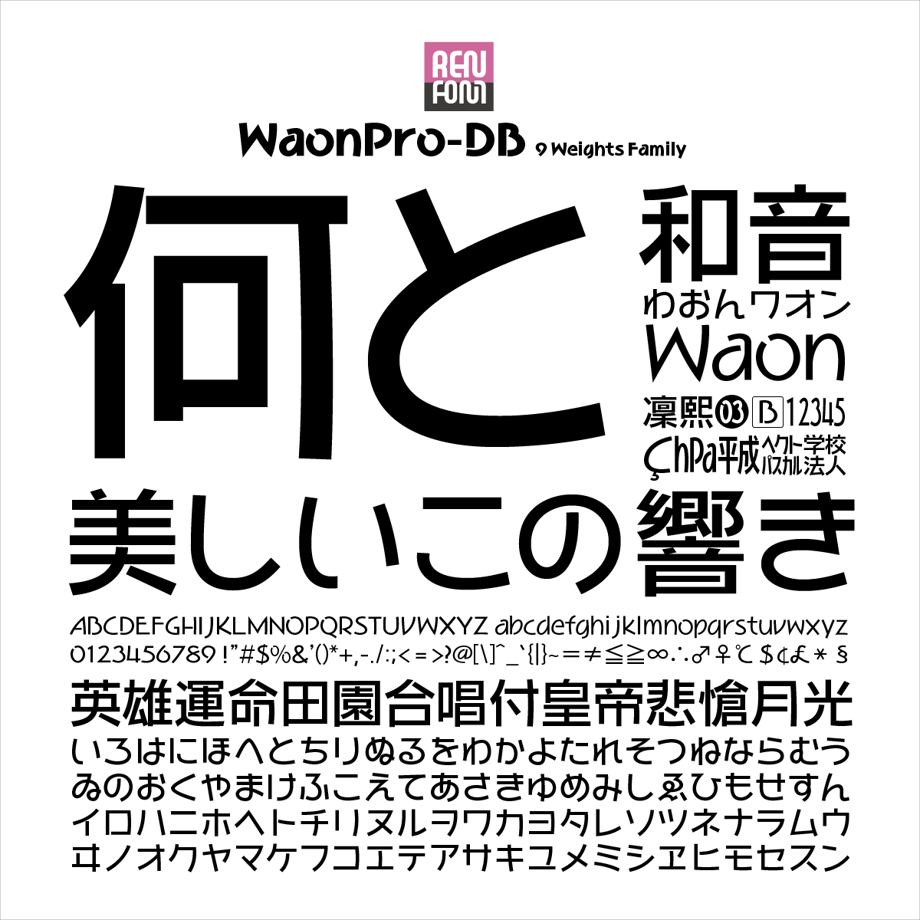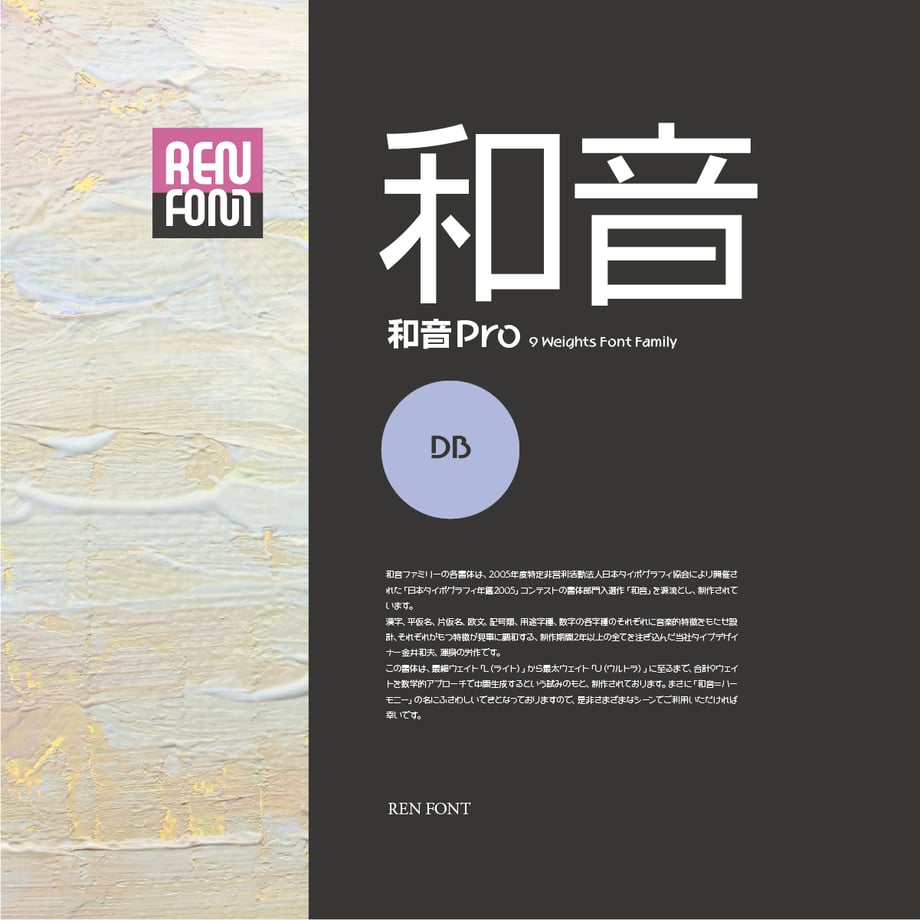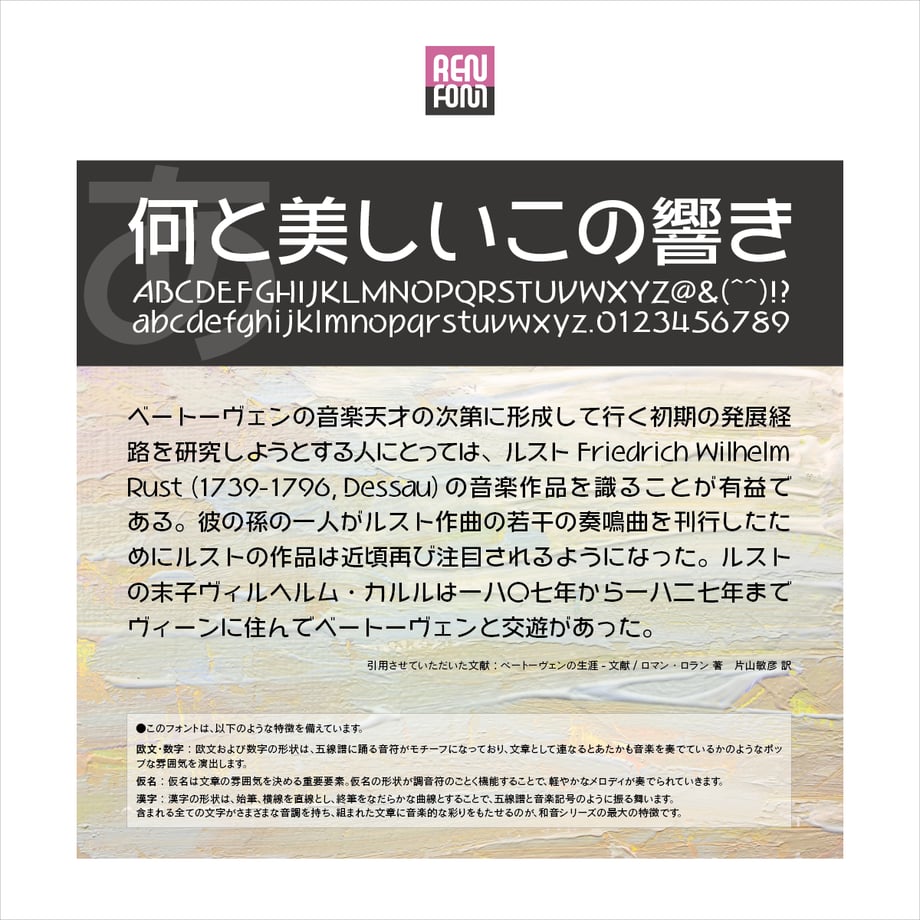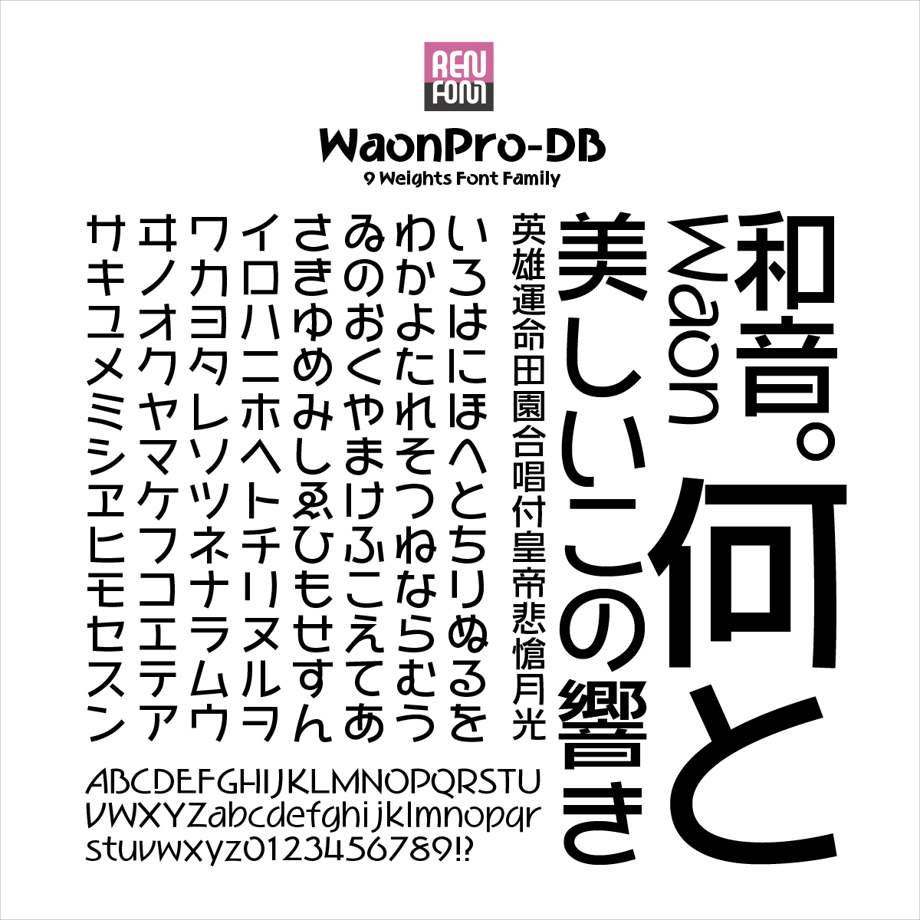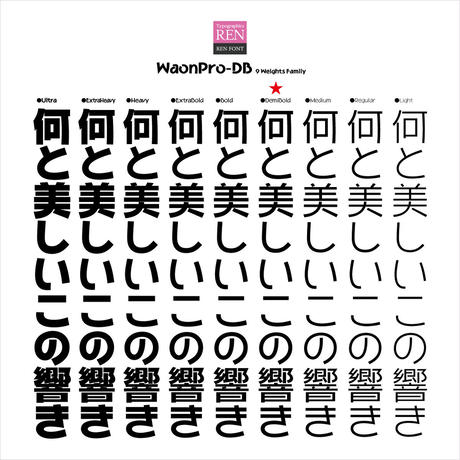
オールマイティな使用感のフォント
和音Pro 9ウェイトファミリー / OpenType
和音ファミリーの各書体は、2005年度特定非営利活動法人日本タイポグラフィ協会により開催された「日本タイポグラフィ年鑑2005」コンテストの書体部門入選作「和音」を源流とし、制作されています。
漢字、平仮名、片仮名、欧文、記号類、用途字種、数字の各字種のそれぞれに音楽的特徴をもたせ設計、それぞれがもつ特徴が見事に調和する、制作期間2年以上の全てを注ぎ込んだ当社タイプデザイナー金井和夫、渾身の労作です。
この書体は、最細ウェイト「L(ライト)」から最太ウェイト「U(ウルトラ)」に至るまで、合計9ウェイトを数学的アプローチで中間生成するという試みのもと、制作されております。まさに「和音=ハーモニー」の名にふさわしいできとなっておりますので、是非さまざまなシーンでご利用いただければ幸いです。
●EH[エクストラヘビー]
●漢字
ほとんどの文字のどこか1か所が切れて離れたデザインになっており、スタッカートのようなアクセント豊かな効果が生まれます。
また、終筆の跳ねをなくして緩やかな曲線しました。これは、指揮者が振り下ろし振り上げるタクトの軌跡を表現しています。 すべての文字に伸びやかさとおおらかさを与え、組まれた文章に音楽的な彩りや愉しさをもたらします。
文章の約70パーセントを占めるといわれる仮名。作品の雰囲気を決める重要要素といって過言ではありません。
音楽に欠かせないリズムを表現するために、終筆をあえて中途半端な長さに終わらせて不安定にし、和音と相反する「不協和音」を表現し、動きを与えました。
まるで音符のように機能し、オペレッタのような、可愛らしく軽やかなメロディが奏でられていきます。
「和音」の基本コンセプトである「文字で音楽を表現する」を、最も端的に文字通りに「表現」しているのがこの従属欧文です。形状は、五線譜に踊る音符がモチーフになっています。とくに「d」「p」は四分音符そのものです。
サンセリフ書体は、一般的にエクスハイトが高めにデザインされています。それにより一文字ひともじが大きめになり、セリフ書体と比べて、現代的な雰囲気が強くなります。「和音」は、さらにエクスハイトを高めにし、大文字と小文字の差があまりありません。また、小文字のふところをより広めにデザインすることで、楽しさ愛らしさを表現しました。
■収録文字 約 15,000 文字
●漢字類
・JIS 第一水準漢字 2,869文字(1区94文字×16区〜46区、および47区49文字)
・JIS 第二水準漢字 厳選2,020文字(1区94文字×48区〜83区、および84区4文字、合計3,294文字の内、あまり使われない文字種1,274文字を除いた当社規定繁用文字種)
●仮名文字種
・基本平仮名 全角・半角全文字
・基本片仮名 全角・半角全文字
・ルビ用仮名字種 全文字
・縦書き用仮名字種 全文字
・横書き用仮名字種 全文字
・プロポーショナル平仮名 全文字
・プロポーショナル片仮名 全文字
・拡張拗音・促音仮名字種 こ・カ・ケ・コ
・拡張濁音仮名文字種 う・ワ・ヰ・ヱ・ヲの各文字の濁音
・拡張半濁音仮名文字種 かきくけこ・カキクケコ・セ・ツ・トの各文字の半濁音
・返し文字種 全文字
・その他リガチャ字種各種
●欧文文字種
・プロポーショナル基本欧文文字種正体 95文字
・プロポーショナル拡張欧文文字種正体 202文字
・半角基本欧文文字種正体 95文字
・半角拡張欧文文字種正体 33文字
・プロポーショナル基本欧文文字種イタリック 95文字
・プロポーショナル拡張欧文文字種イタリック 202文字
・90度時計回り回転欧文字種 上記分すべて
・全角ギリシャ文字種正体 48文字
・全角キリル文字種正体 66文字
・全角欧文類正体 62文字
・その他リガチャ欧文各種
●用途数字字種 ●記号類 ●罫線類 ●用途字種類